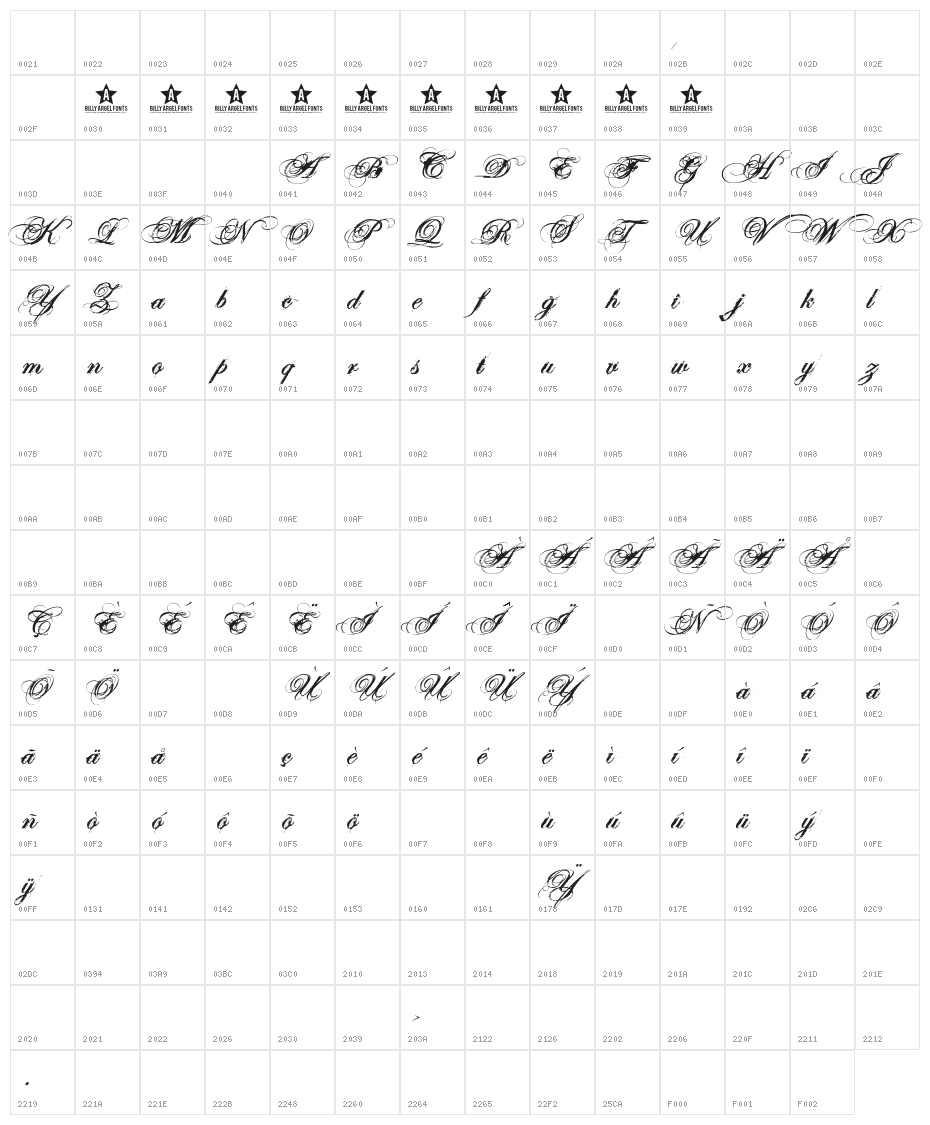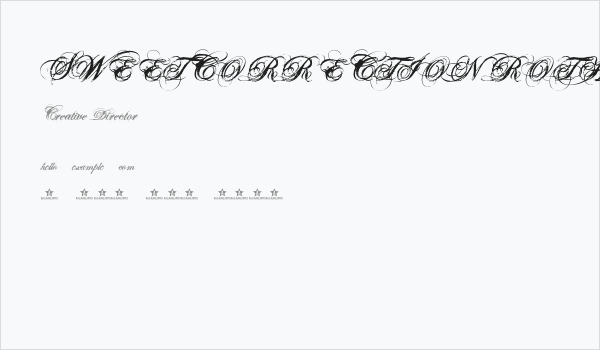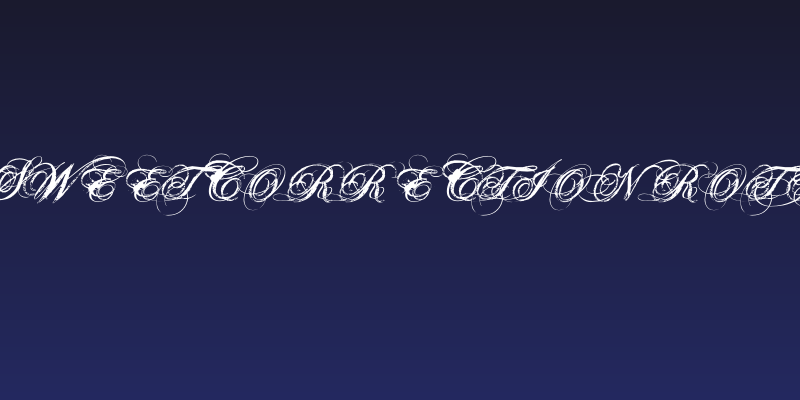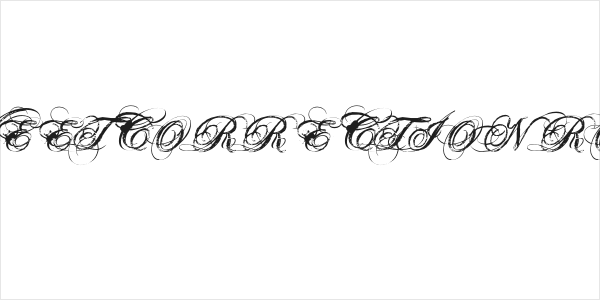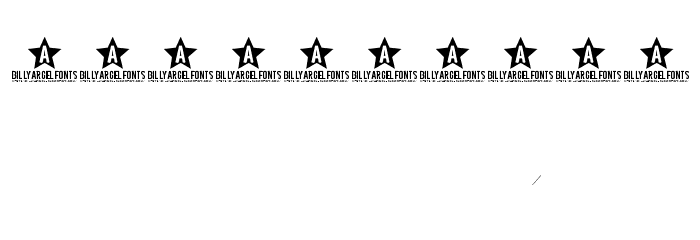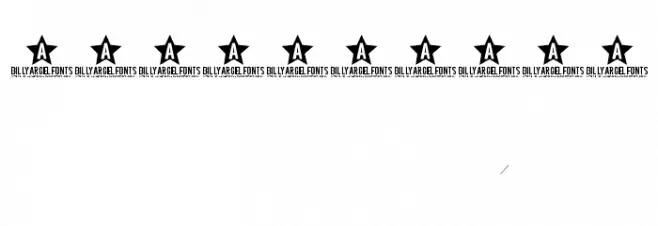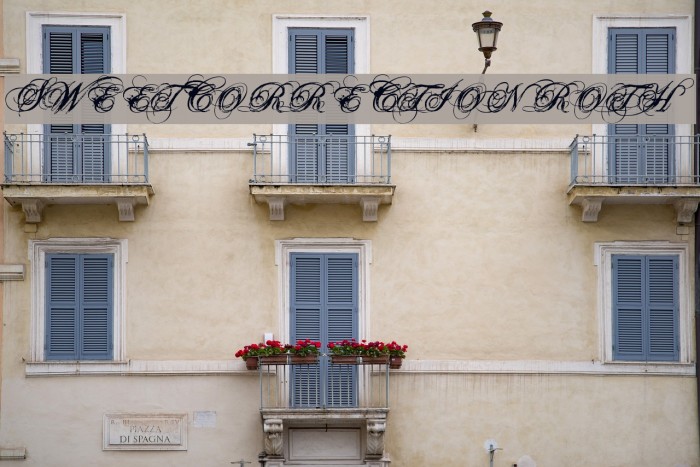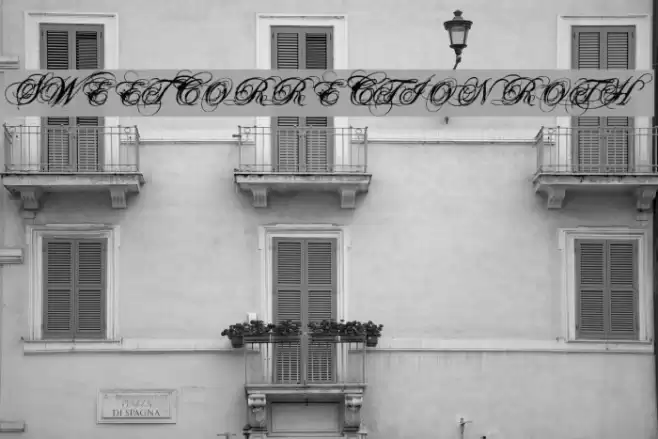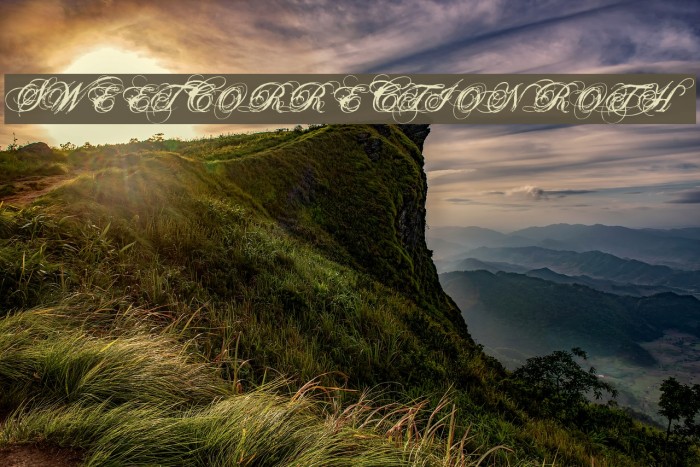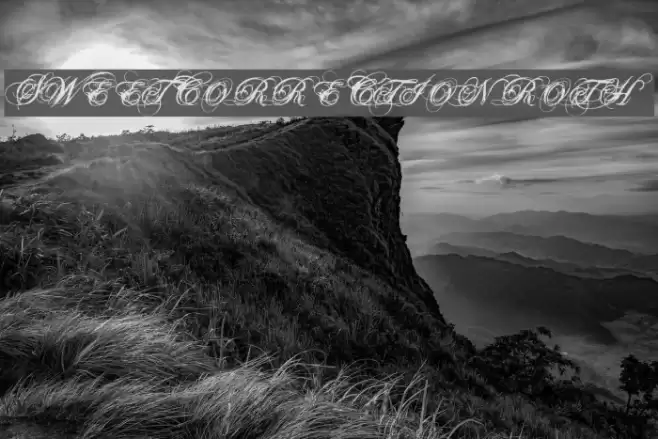
SWEETCORRECTION ROTH Font
✎ Calligraphic
| Kategorien | Calligraphic |
| Gesamtstil | Vintage, Decorative |
| Anwendungsfall | Logos, Invitations, Artistic Posters |
| Vorgeschlagene Projekte | Ideal for wedding invitations, branding for luxury products, artistic posters, and any project requiring a touch of elegance and uniqueness. |